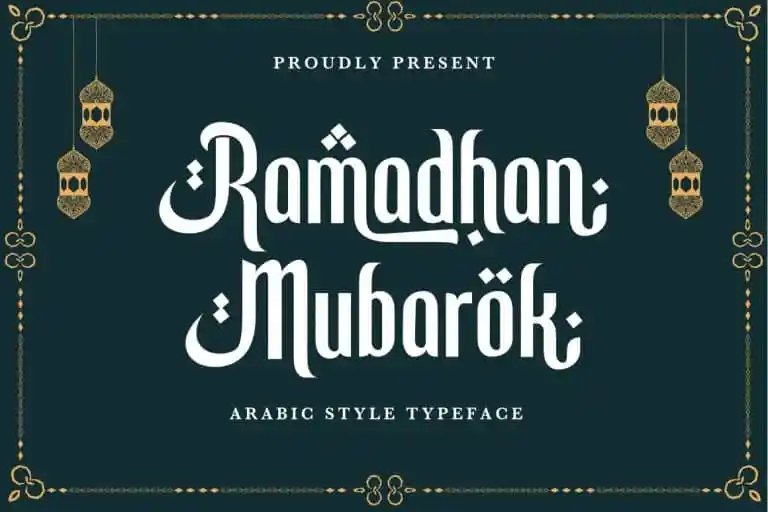
Ramadhan Mubarok Display Font – Download Grátis
Introduzimos Ramadhan Mubarok Display Font, uma nova fonte de estilo islâmico para uso em aplicações visuais digitais. Foi projetada com técnicas de tipografia digital e flat-pen, oferecendo um visual elegante às letras. Este design é perfeito para vários tipos de produtos, incluindo roupas, camisetas, produtos alimentícios e bebidas, capas de livros, revistas, posters, flyers e outros projetos gráficos. Ramadhan Mubarok Display Font traz uma aparição arrojada e moderna aos textos, ideal para marcasar visuais que precisam de um toque especial. Com sua estética elegante e sofisticada, esta fonte é perfeita para designers e freelancers que desejam incluir elementos distintivos em seus projetos gráficos. Seja em uma camiseta casual ou em um postero publicitário, Ramadhan Mubarok Display Font oferece a opção de deixar seu design mais chamativo e memorável.